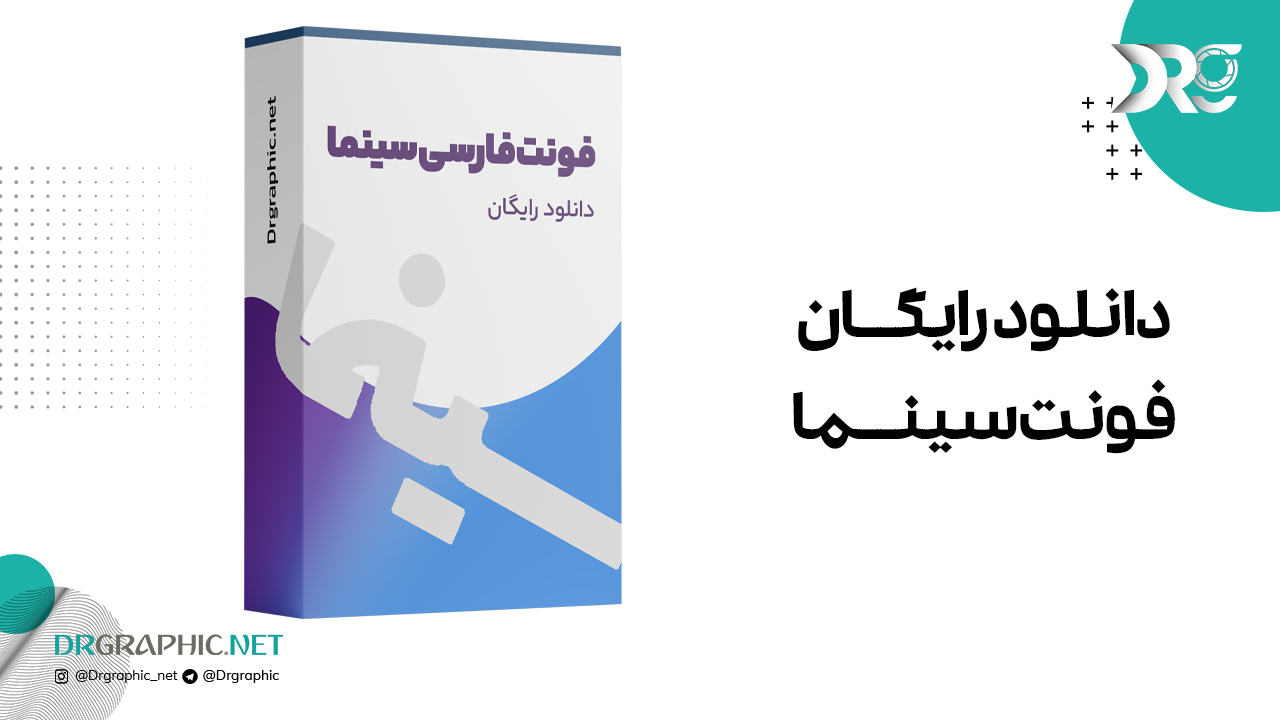
فونت فارسی سینما
فونت فارسی سینما از سری فونت‌های فارسی است که می‌تواند در طراحی‌های مختلف به عنوان فونت ضخیم و برای تیترنویسی مورد استفاده قرار گیرد. این فونت را می‌توانید به صورت رایگان در پایان همین صفحه دانلود نمایید .
این فونت ، یک فونت کلاسیک است ، که پیش و قبل از انقلاب بیشتر در مجلات و فیلم های ایرانی آن زمات مورد استفاده قرار می گرفت. فونت سینما برای طراحی های با هر موضوعی مناسب بوده و در عین سادگی جلوه خاصی به کارهای گرافیکی شما می بخشد.
• مناسب تیترنویسی در انواع طراحی ها
• طراحی با کیفیت و ضخیم
• فونت فارسی دارای خوانایی بالا
• دارای تمام حروف و اعداد فارسی